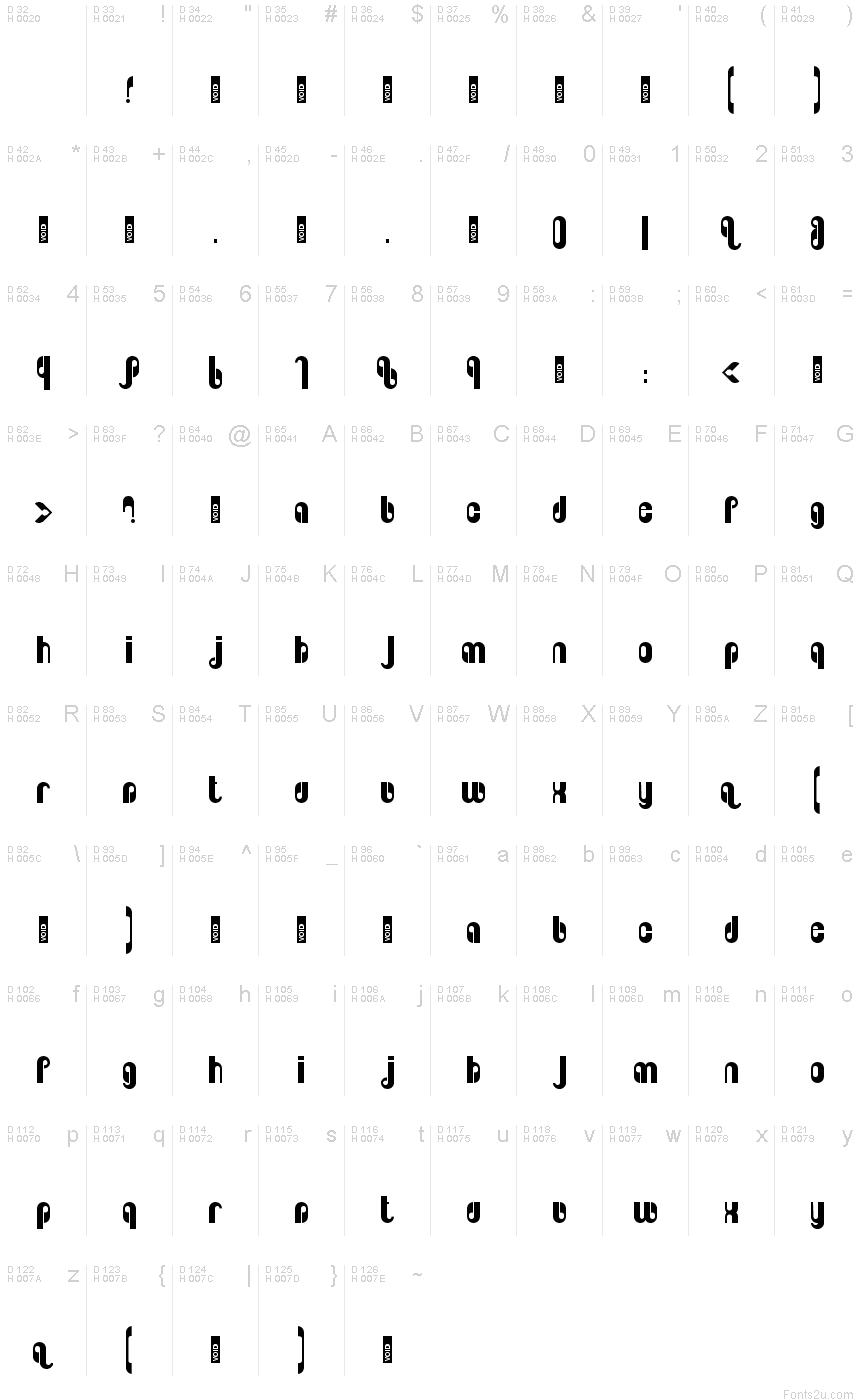
Pseudolux è un carattere display gratuito e groovy con la geometria arrotondata delle scritte della fine degli anni Sessanta. I tratti ampi si curvano in ganci stretti e forme chiuse, conferendo alle lettere una struttura compatta, quasi modulare. Archi ripetuti e verticali smussate mantengono il design visivamente coerente.
Le copertine degli album sono il suo contesto ideale, in particolare per uscite funk, soul o psichedeliche. Anche i manifesti di festival e il branding nel settore della moda si sposano con il suo stile d'epoca. Le curve intrecciate possono diventare parte di illustrazioni per packaging retrò o di un motivo per copertine di dischi, piuttosto che fungere da semplice testo.